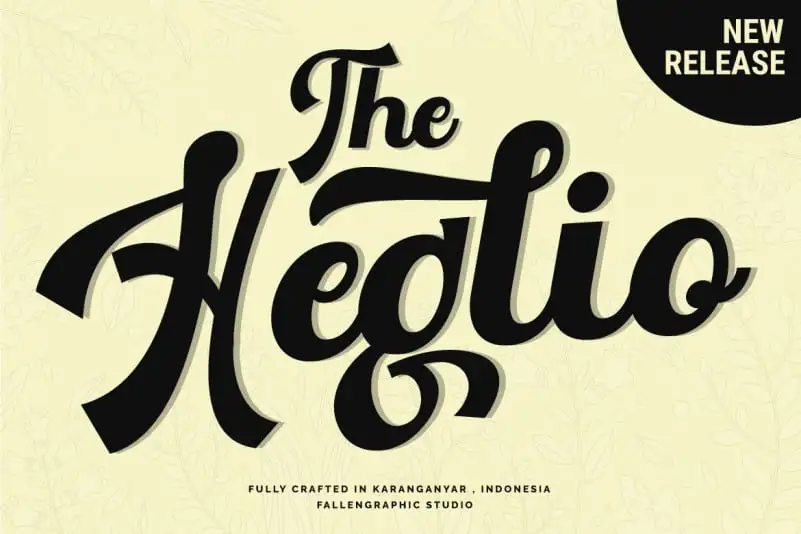
A Fonte Calligrafia Heglio é uma excelente opção para designers que buscam uma fonte elegante e sofisticada. Esta chamada de arte foi criada pela equipe do estúdio designado FallenGraphic Studio, inspirada nos antigos sinais da loja de bar e cabeleireiro. O resultado final resulta em um tipo clássico com um ar elegante, perfeito para projetos modernos ou clássicos. A Heglio se adequa perfeitamente a uma variedade de aplicativos, desde logotipos e rótulos até cartões de visita, embalagens, selos, capas de livros e até mesmo arte impressa em camisetas. Seja para uma marca inovadora ou um design clássico, Heglio é uma fonte versátil e poderosa que não pode ficar fora da sua biblioteca de tipos.